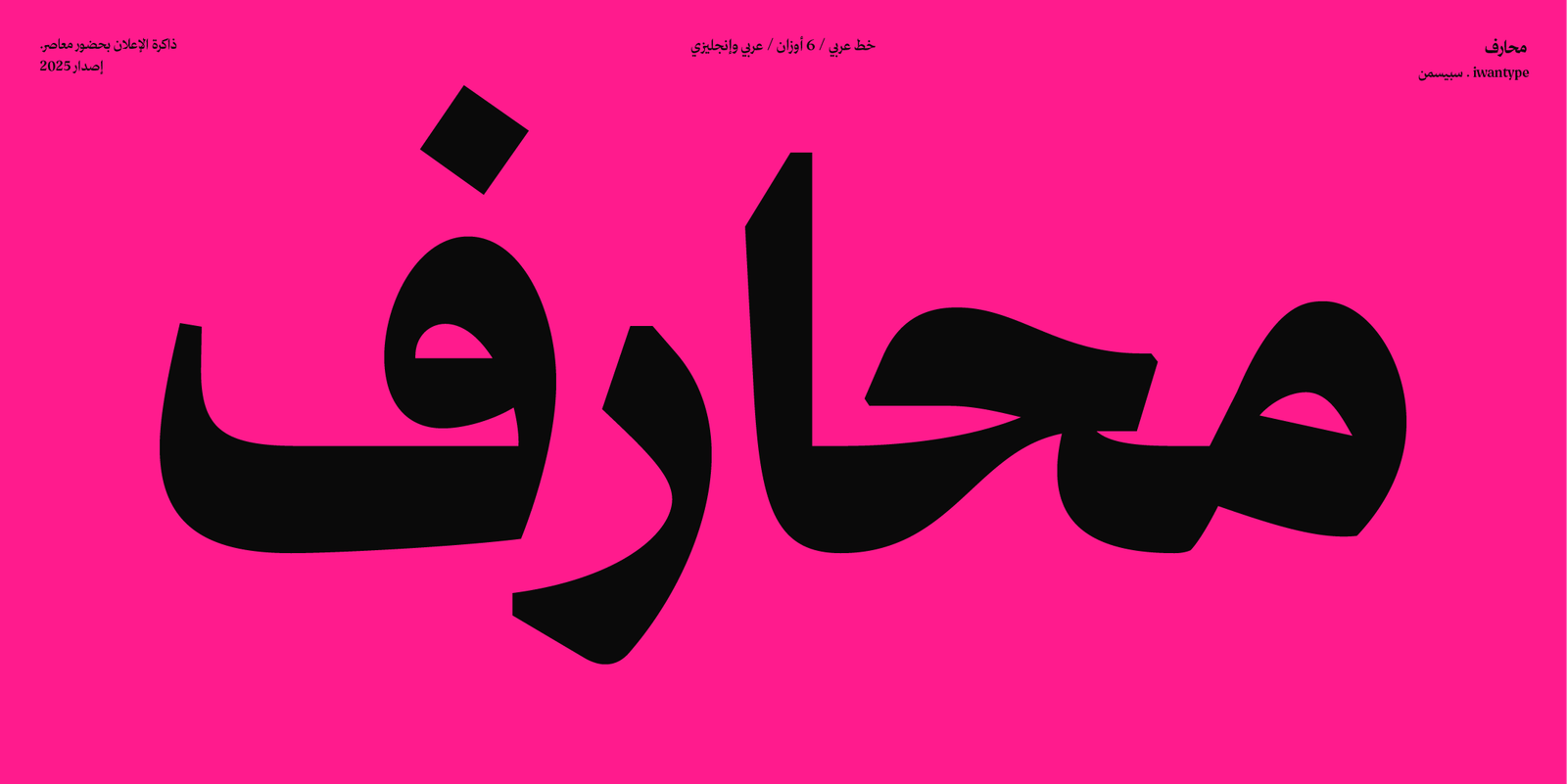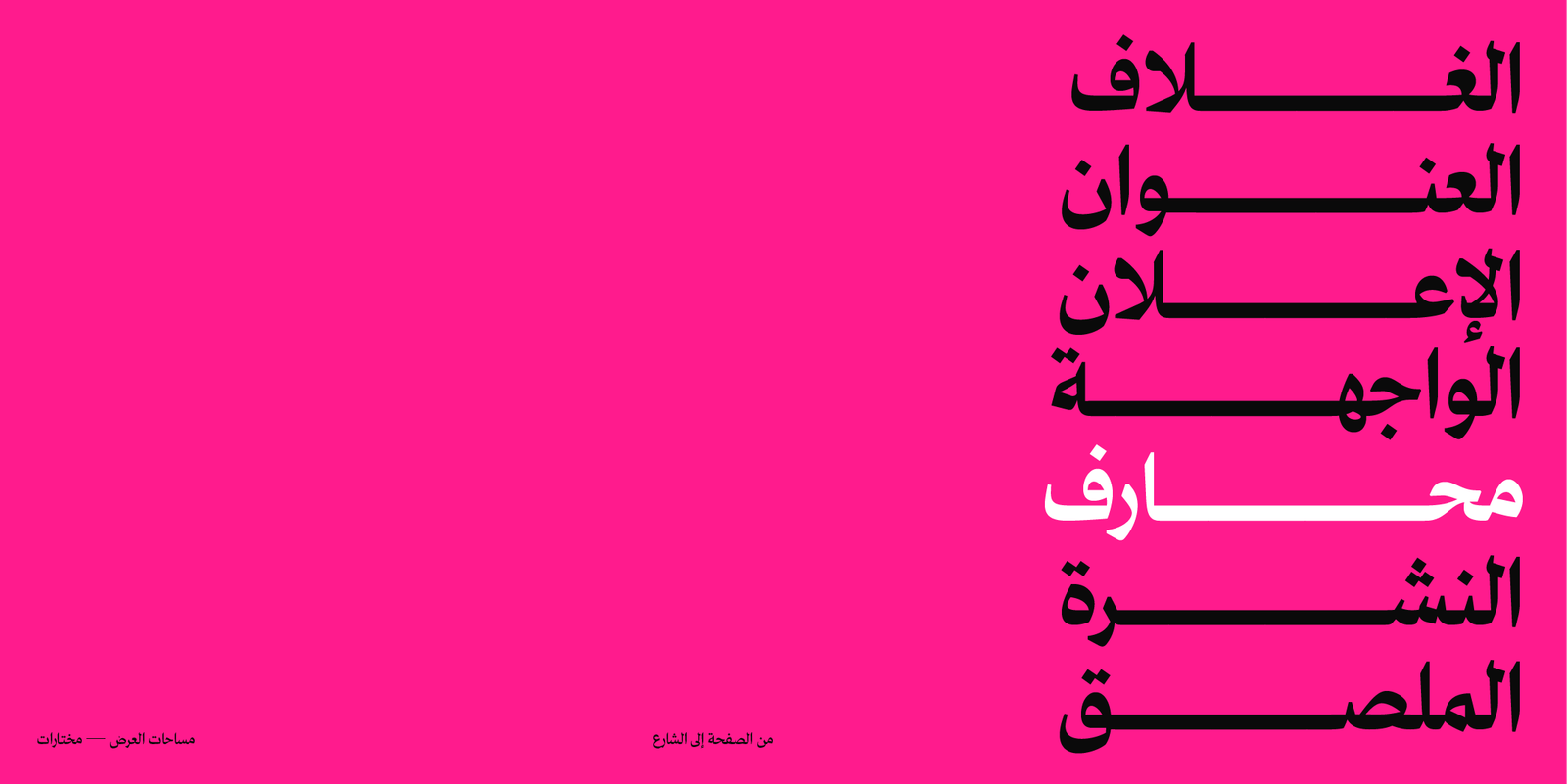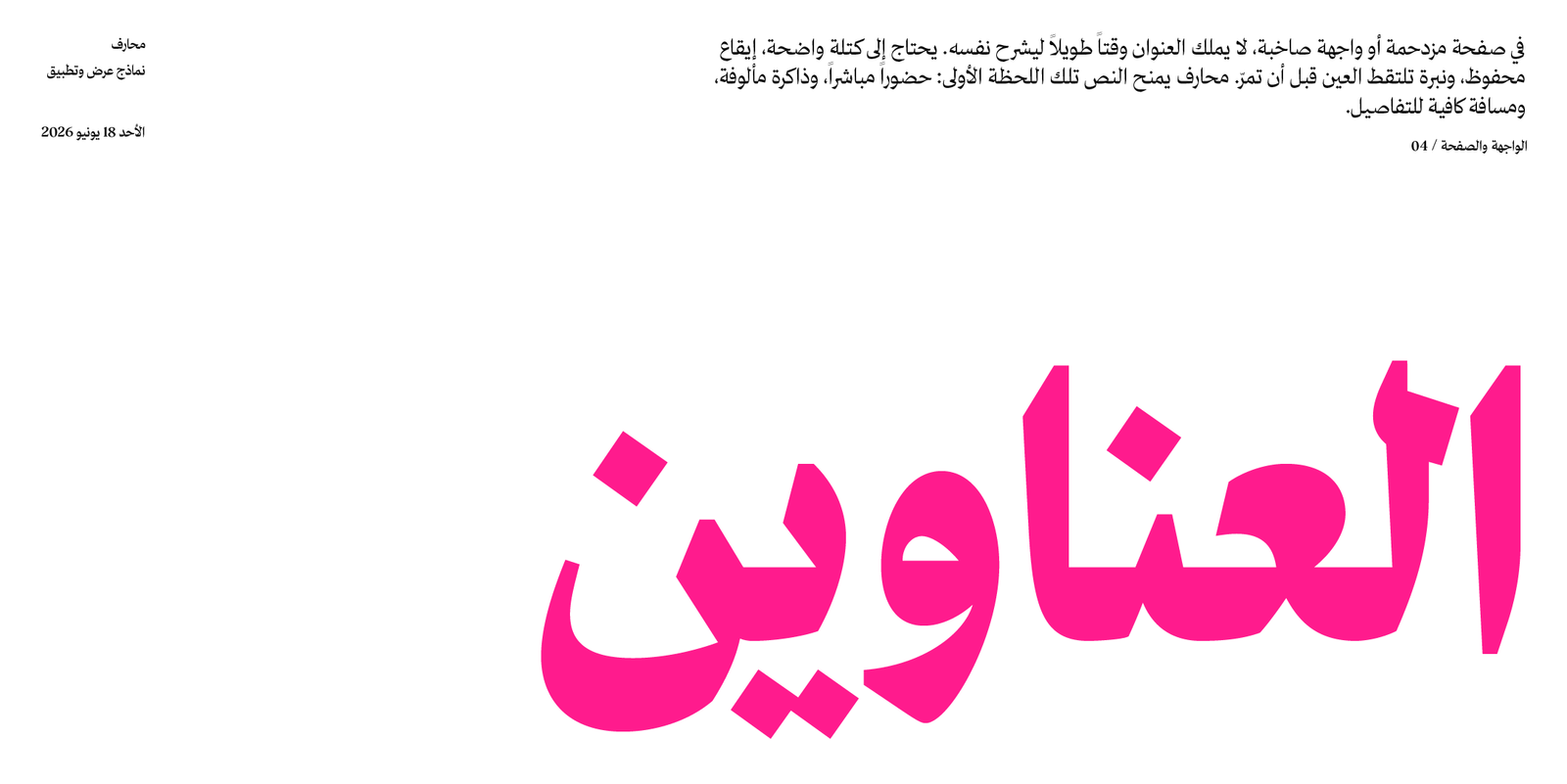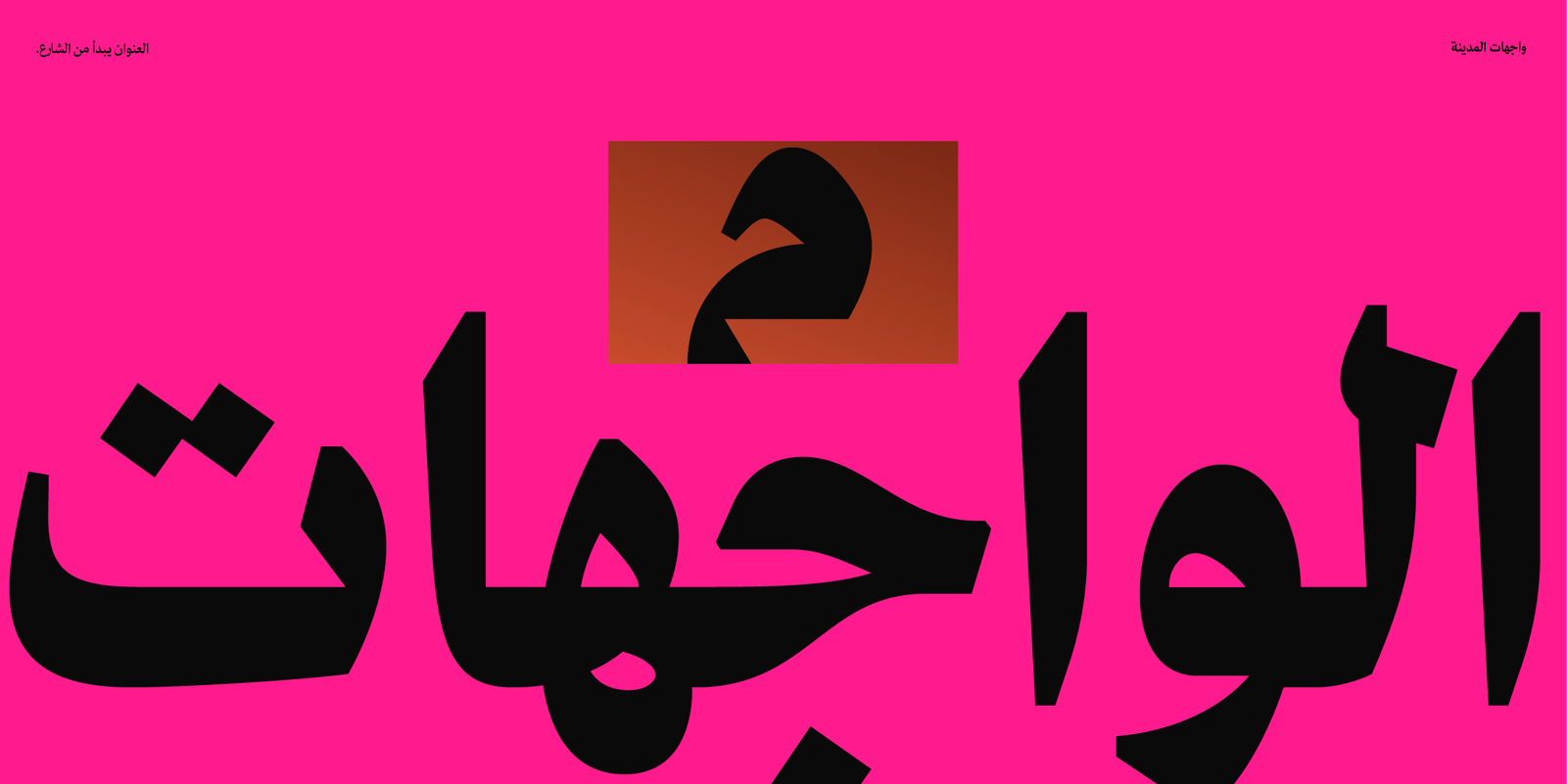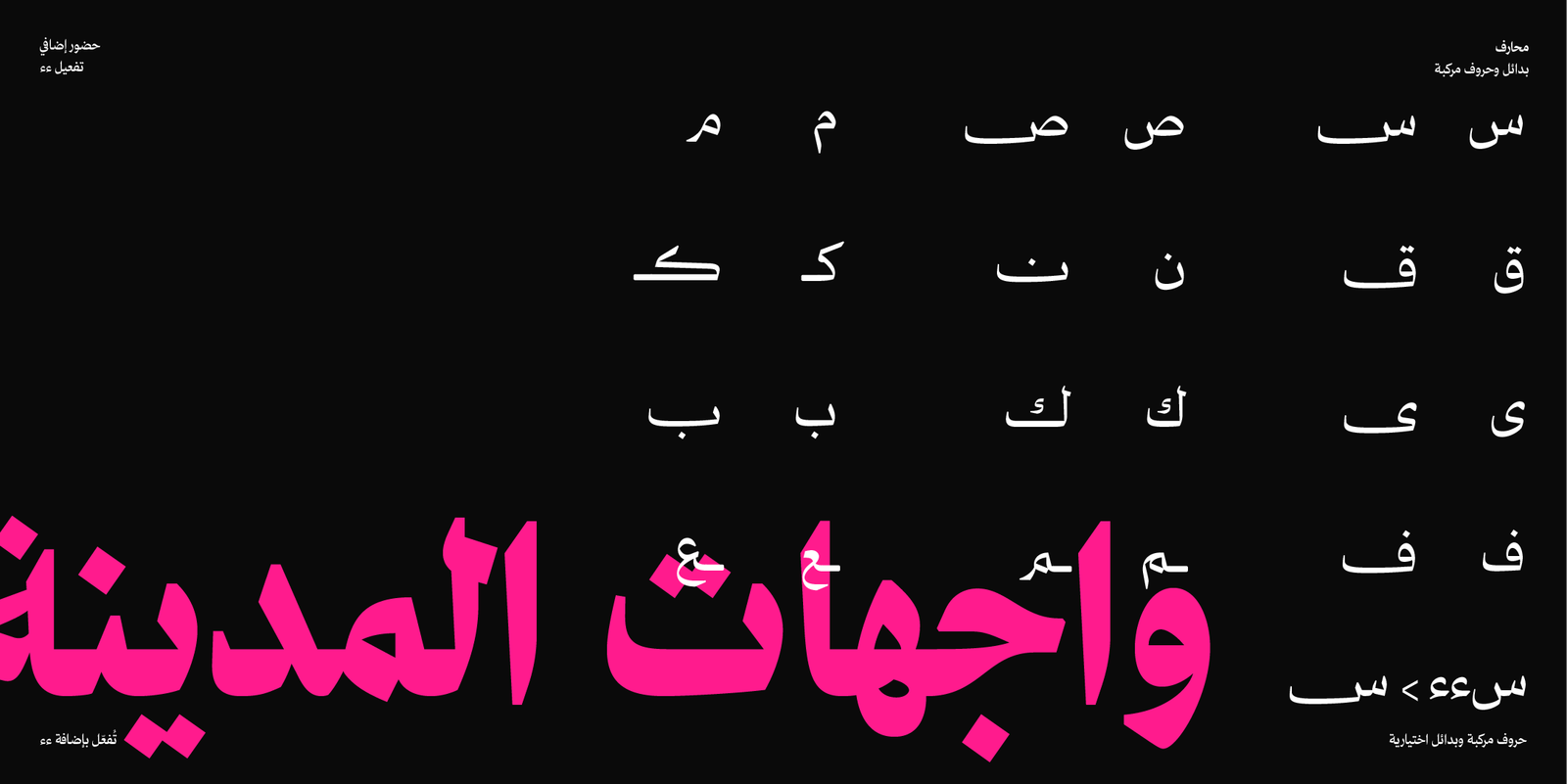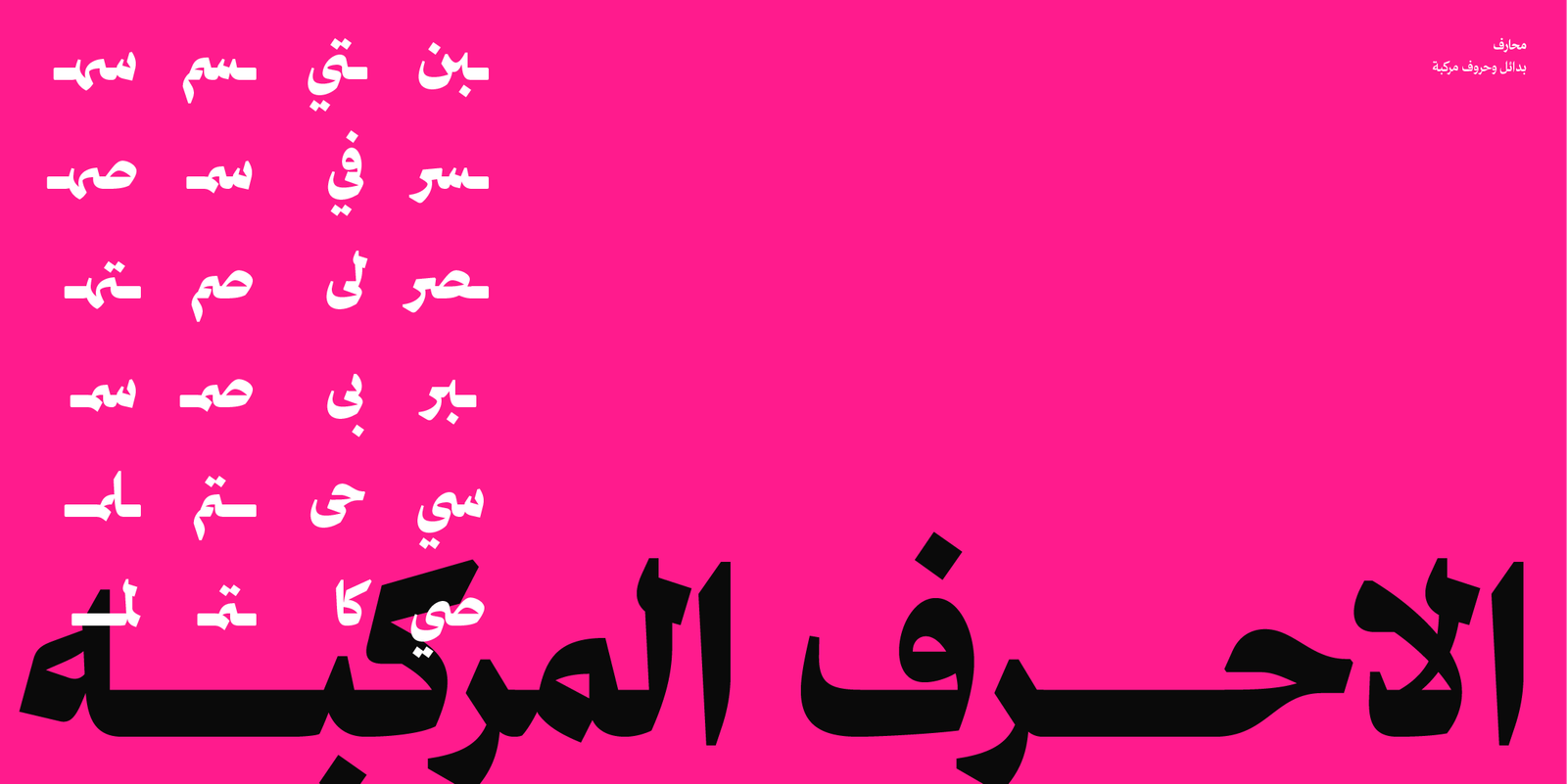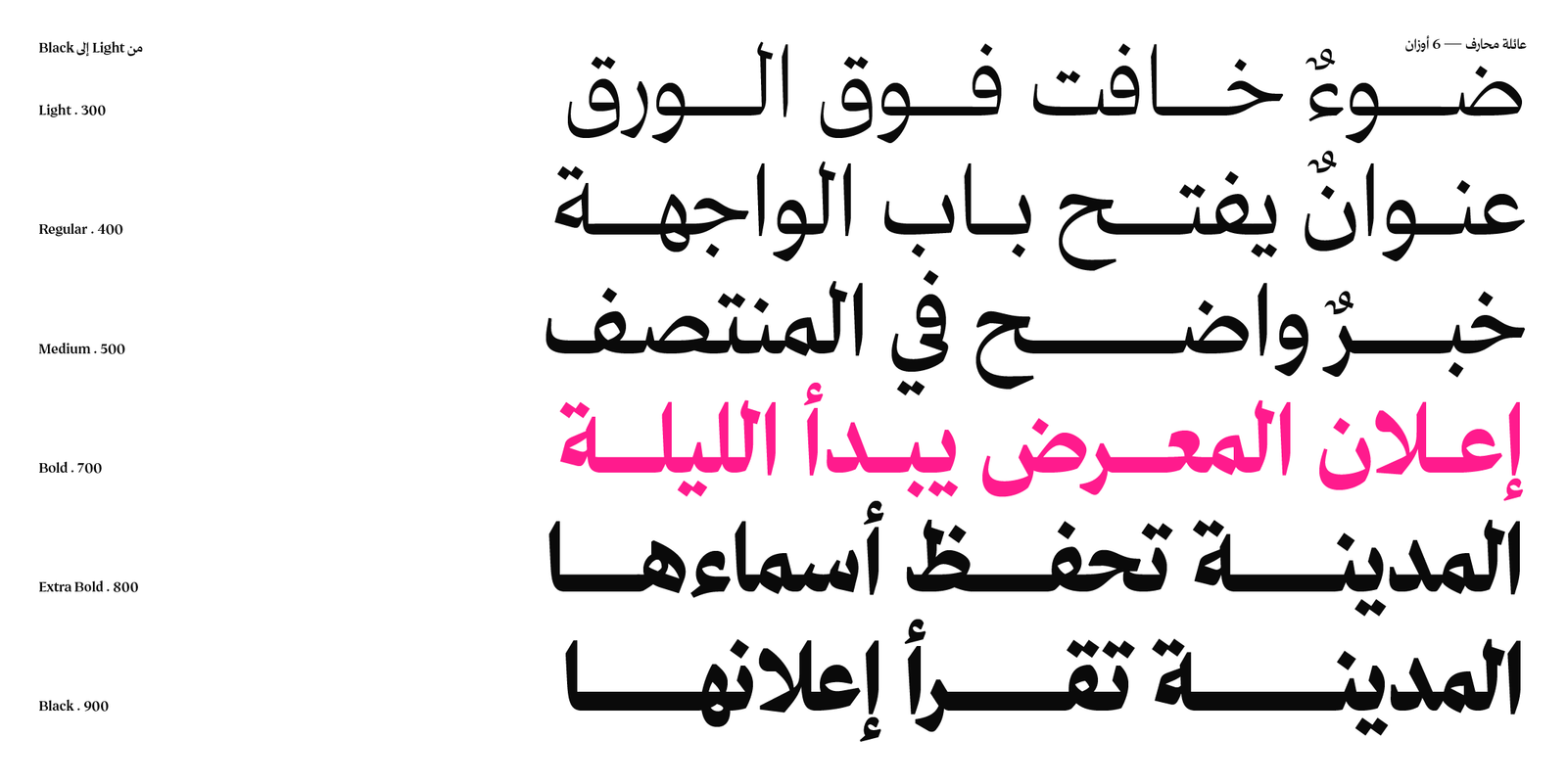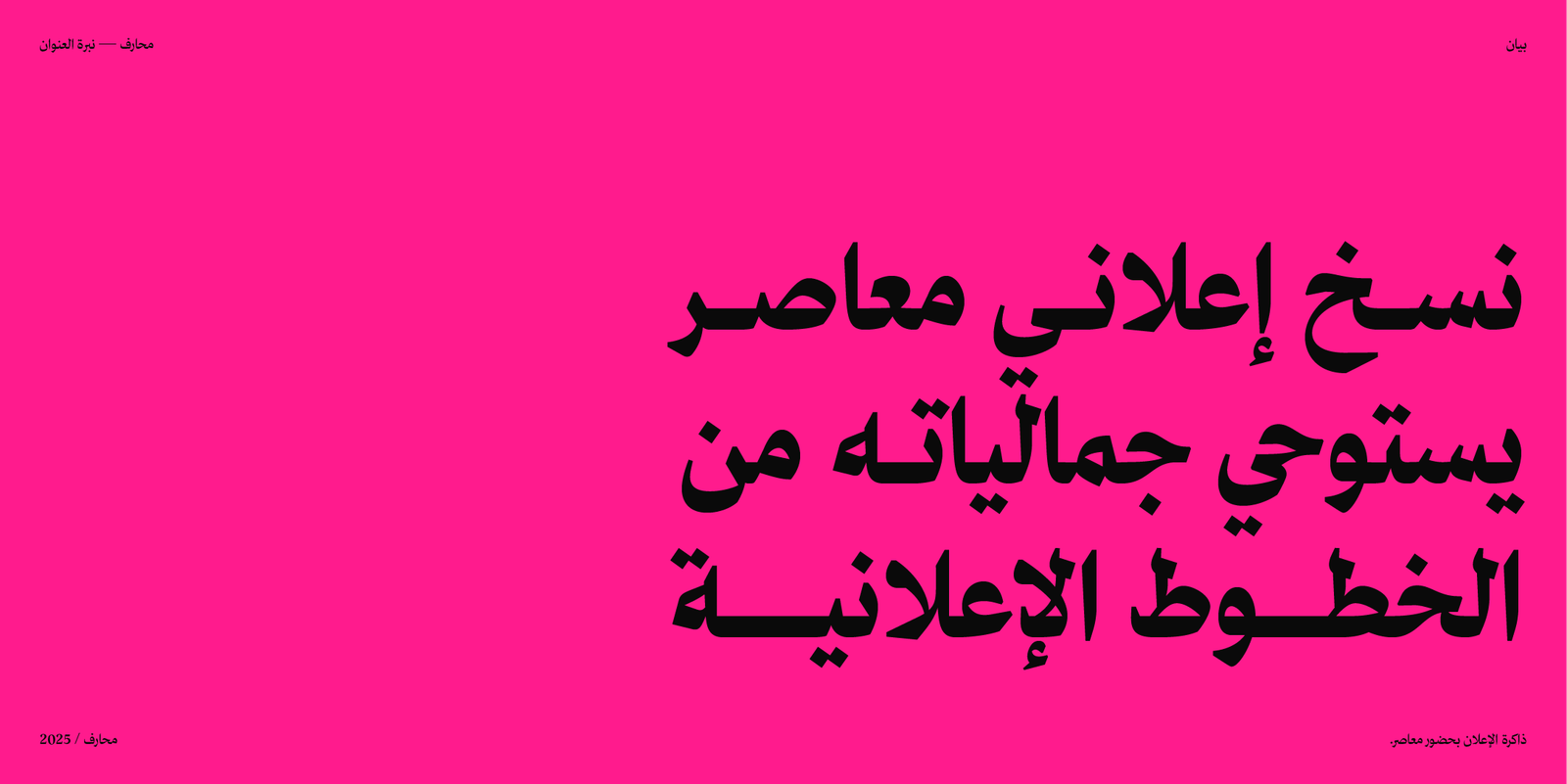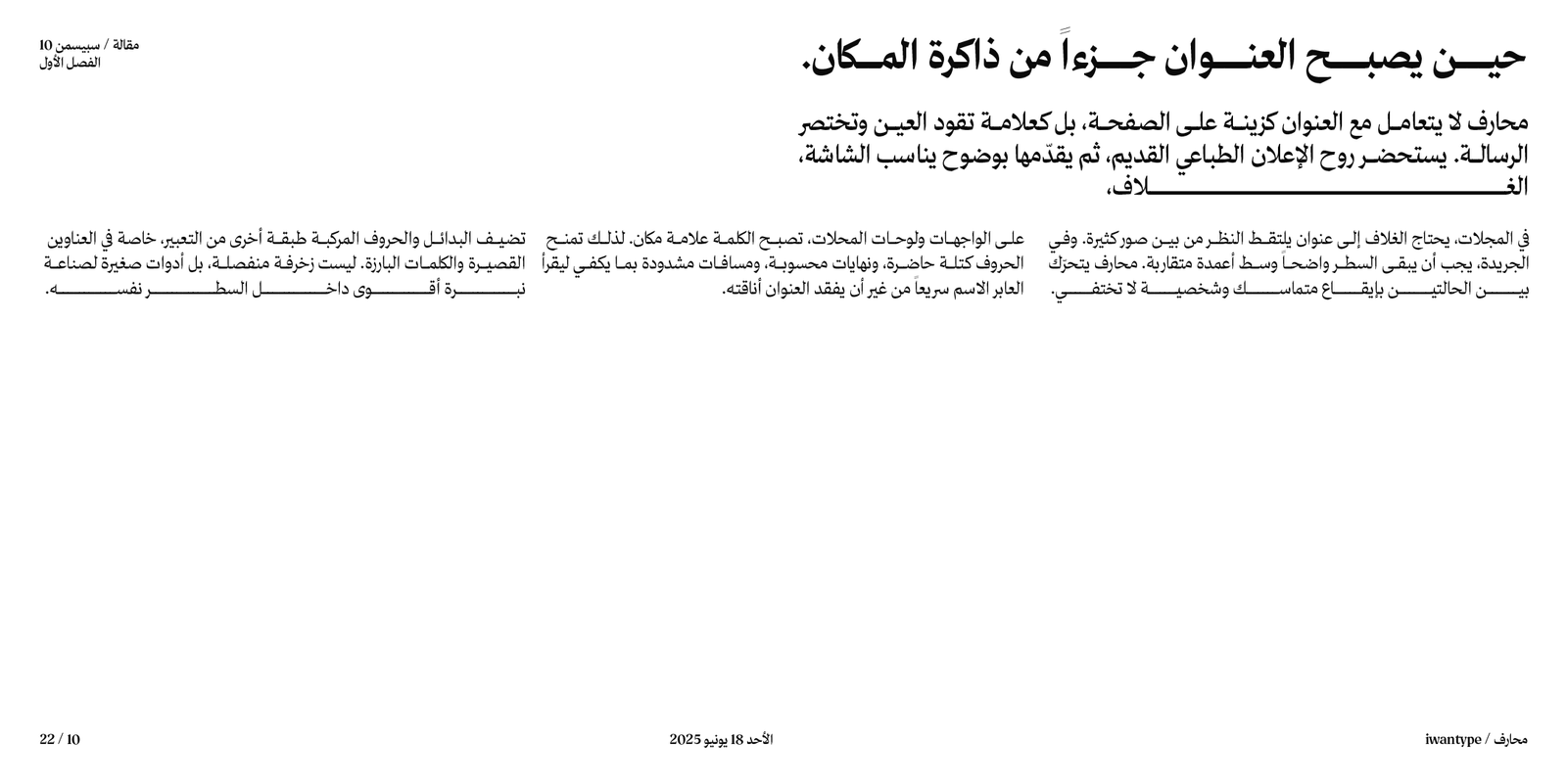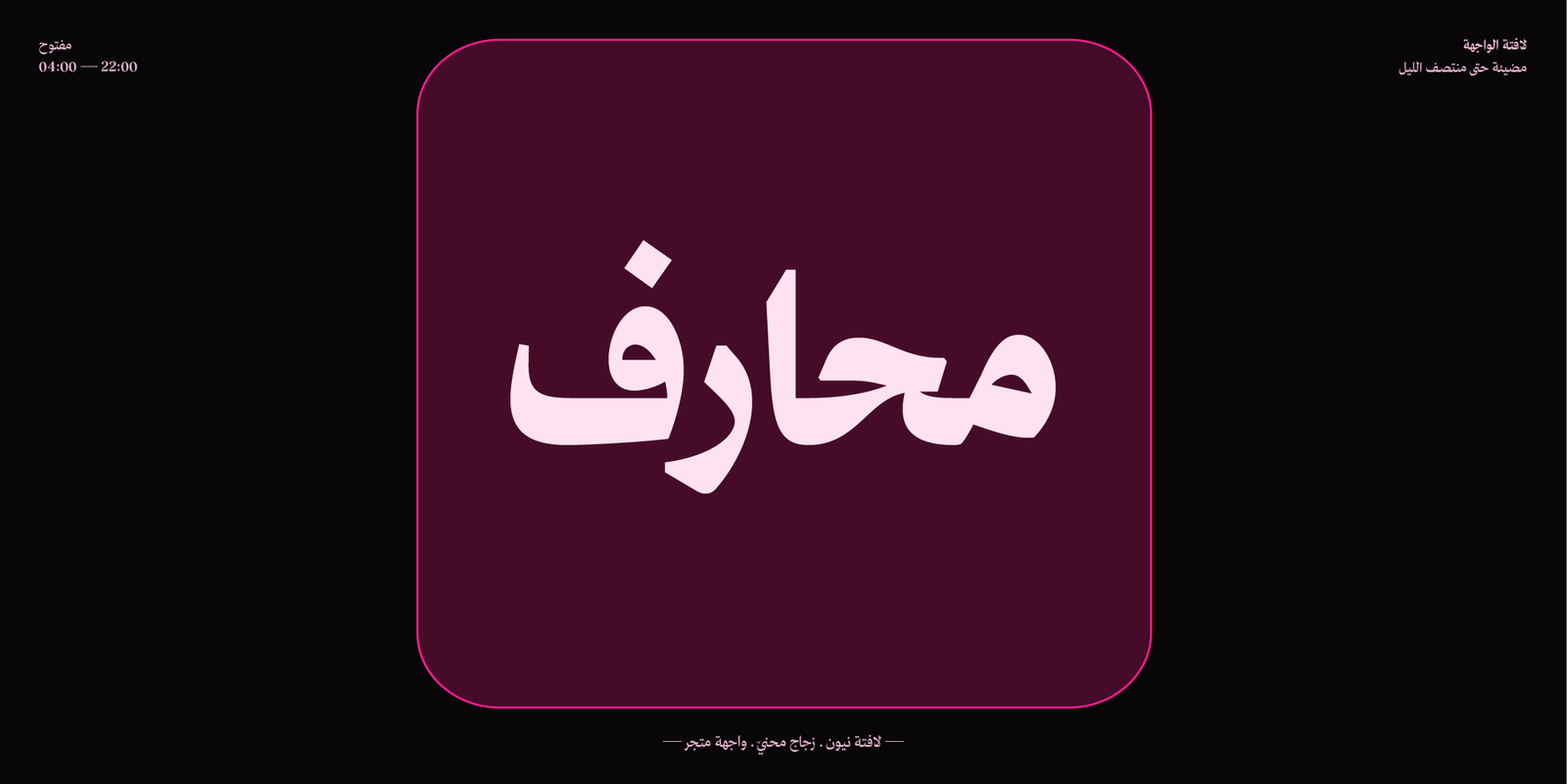
خط محارف – نسخ – Maharif Typeface
خط محارف – نسخ إعلاني حديث – Maharif Typeface
خط عربي طباعي معاصر يجمع بين جماليات الخطوط الإعلانية التقليدية والطابع الحديث.
استُلهم تصميمه من الخطوط الإعلانية التي كانت تُستخدم في المجلات، الجرائد، الإعلانات التجارية، ولوحات المحلات الكلاسيكية.
يُعيد “محارف” إحياء هذه الأساليب الكلاسيكية مع لمسات حديثة تلبي احتياجات التصميم المعاصر.
مميزات خط محارف
يتضمن الخط العديد من مزايا OpenType التي تضفي عليه مرونة وتنوعًا في الاستخدام، مثل:
- أحرف مرسلة (تُفعَّل بإضافة “ءء” بعد الحرف)
- أحرف مركّبة تُحسّن سلاسة التراكيب وتناسق النص.
- 6 أوزان كاملة تمنح مرونة واسعة في الاستخدام الطباعي.
- يدعم رمز الريال السعودي والريال العُماني ،ويتم تفعيلهما تلقائيًا عند كتابة الاختصارات: ر.س للريال السعودي ر.ع للريال العُماني